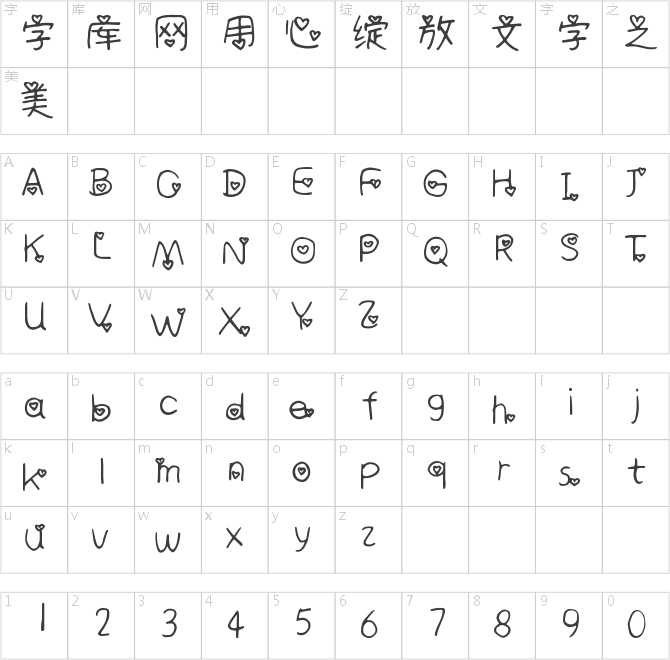
倉(cāng)耳秘之果
倉(cāng)耳字庫(kù)
倉(cāng)耳秘之果字體字庫(kù)是一款讓人賞心悅目、百看不厭的中文字體,適合各類廣告和產(chǎn)品包裝設(shè)計(jì)應(yīng)用,字體大小6.02MB,格式為ttf字體,上傳用戶是東情,作者/版權(quán)方為倉(cāng)耳字庫(kù)